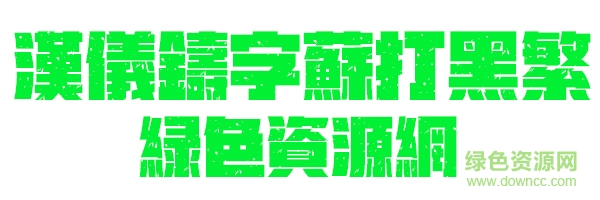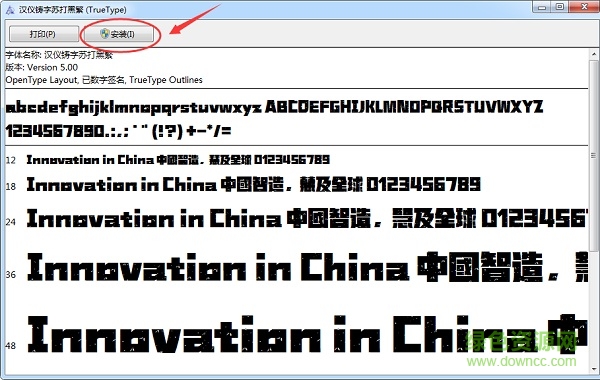
漢儀鑄字蘇打黑繁體是一個(gè)免費(fèi)的繁體字體。這款漢儀字體比較規(guī)范,有點(diǎn)像放大版的黑體字體!無論是用來設(shè)計(jì)廣告還是海報(bào)等作品都很不錯(cuò)!喜歡繁體字的朋友快來綠色資源網(wǎng)下載體驗(yàn)吧。
字體語言:繁體中文
包含字?jǐn)?shù):7519
字體風(fēng)格:力量;趣味
字體用途:廣告
字重:常規(guī)